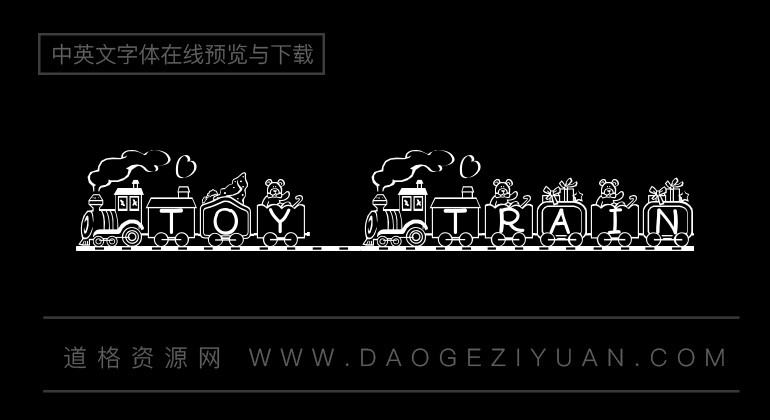
Toy Train 是一款具有童趣特色的字体,它的字形简洁大方,字体细节清晰可见,能够带来美观的视觉效果。Toy Train 字体的特点是其简单的设计,字形精致,笔画流畅,可以让文字表达更加生动有趣。此外,Toy Train 字体还具有可爱的童趣设计,可以很好地表达出童年的欢乐和自由。内容介绍
Toy Train是一款非常不错的手写艺术字体,具有很好的视觉感,适合于文化类的宣传设计、商业类品牌的广告和产品包装设计以及个性化文字排版等较多场景。